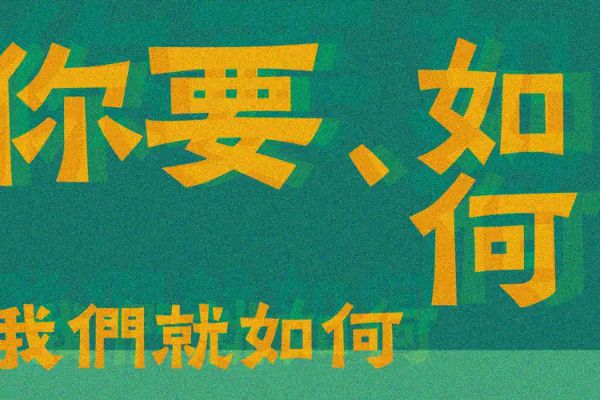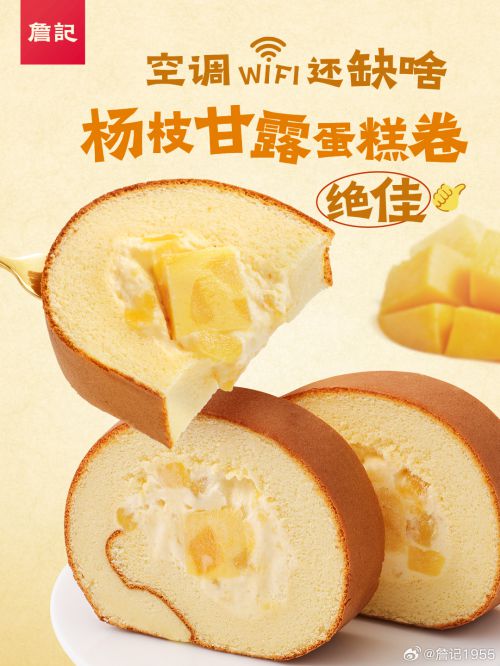
点字金刚隶
【点字金刚隶】是一款融合中国风与力量感的创意字体,由点字库精心打造,支持简体/繁体中文,适用于会员商用授权。字体在承袭隶书优雅韵味的基础上创新,以方正字形构建沉稳骨架,重心居中平稳,中宫宽博大气,兼具端正现代的视觉效果与豪放爽朗的气势。 点字金刚隶的笔画设计粗重均匀,方头收尾搭配几何化装饰元素,既保留隶书的古典韵味,又注入现代设计的硬朗质感。笔画间巧妙断开的处理增强了字体的节奏感,几何结构的运用则凸显恢弘力量,整体呈现出刚柔并济的视觉张力。 无论是标题设计、品牌LOGO还是文化宣传场景,点字金刚隶均能以其独特的古典力量感脱颖而出,为设计作品赋予深厚的文化底蕴与强烈的视觉冲击力,是艺术创作与商业应用的理想选择。